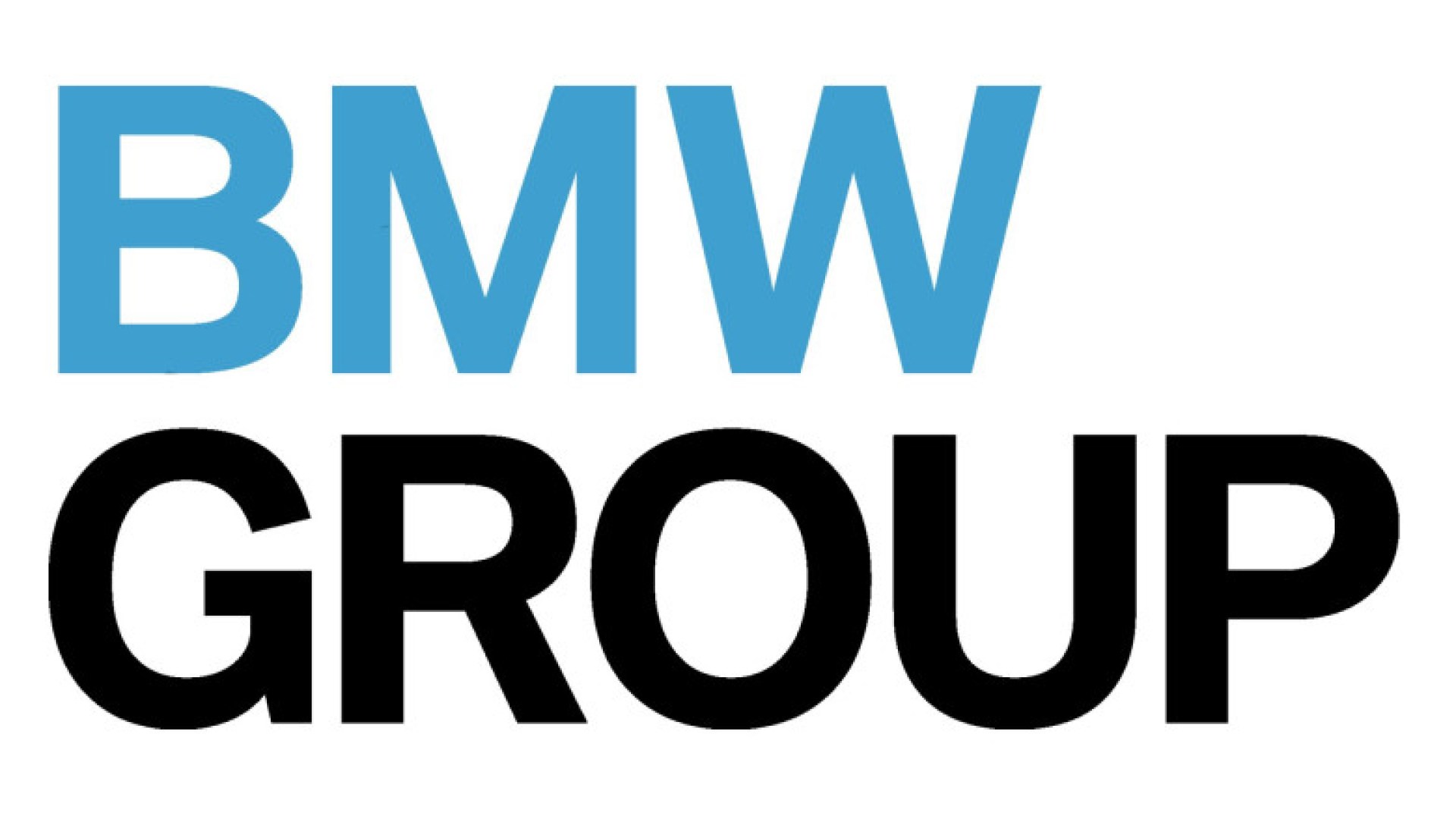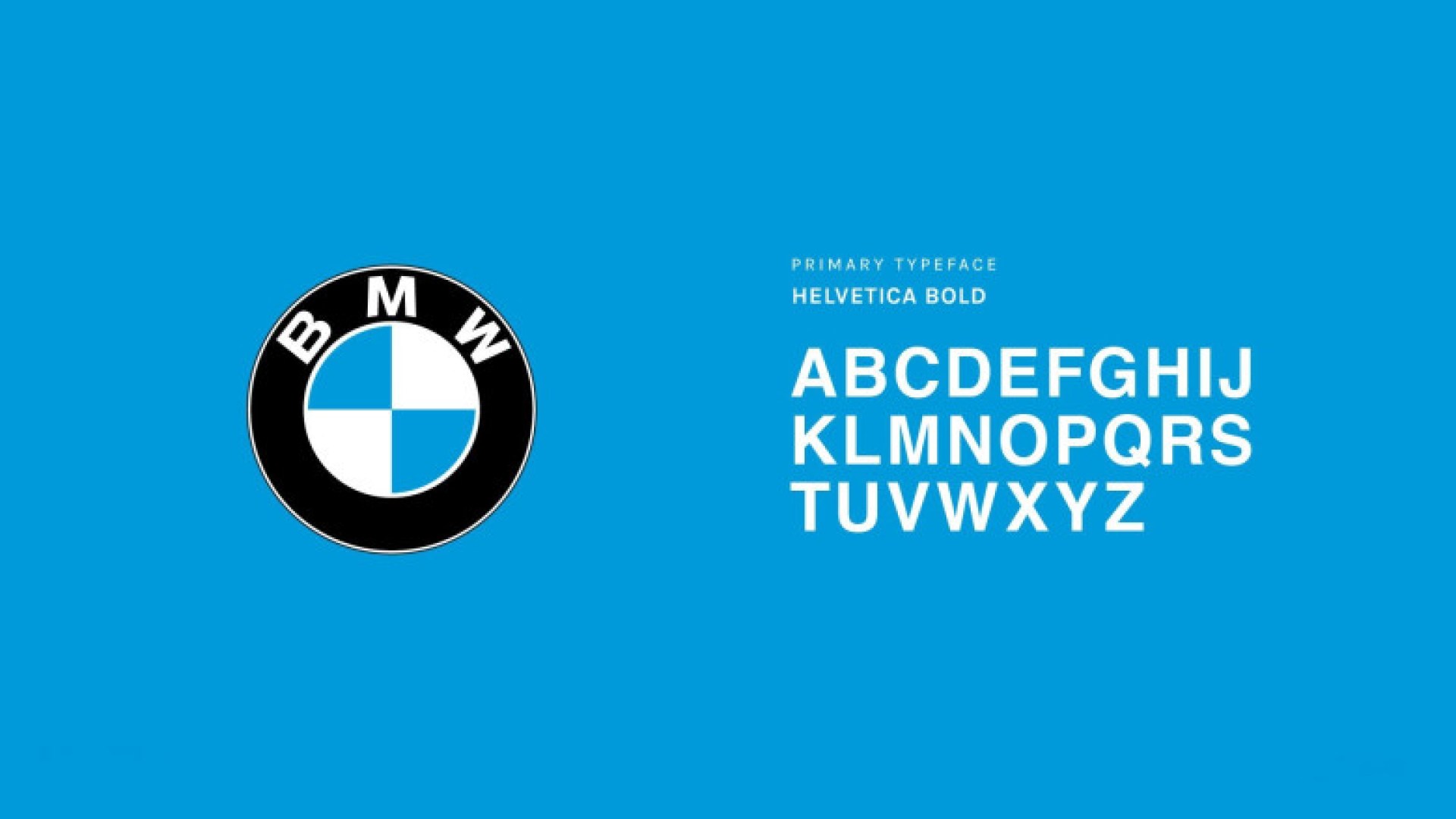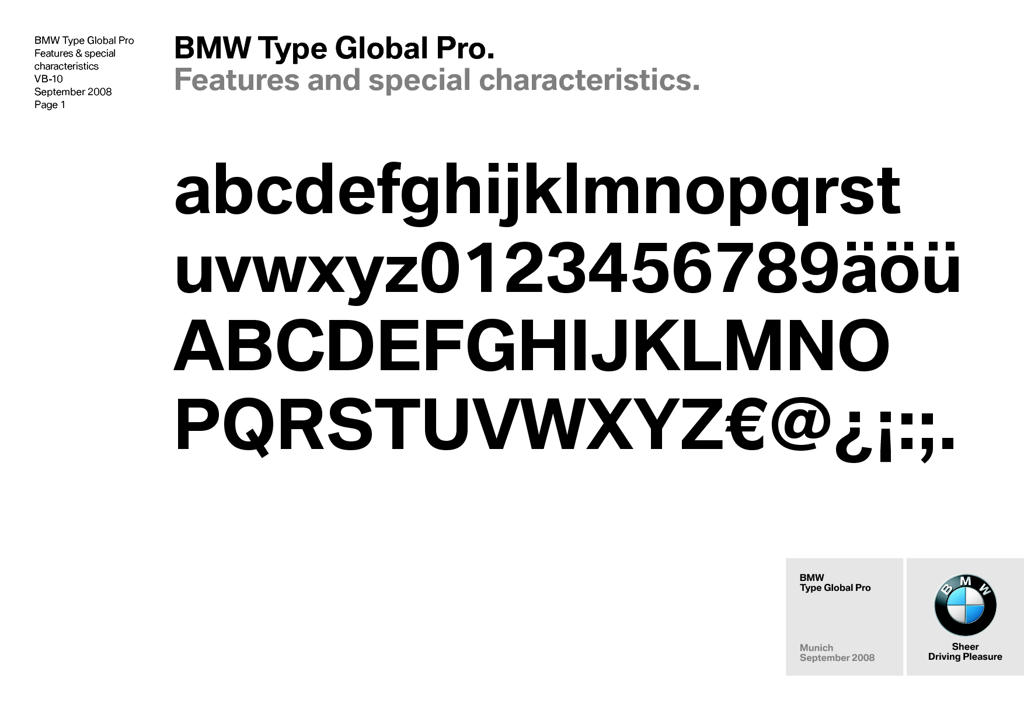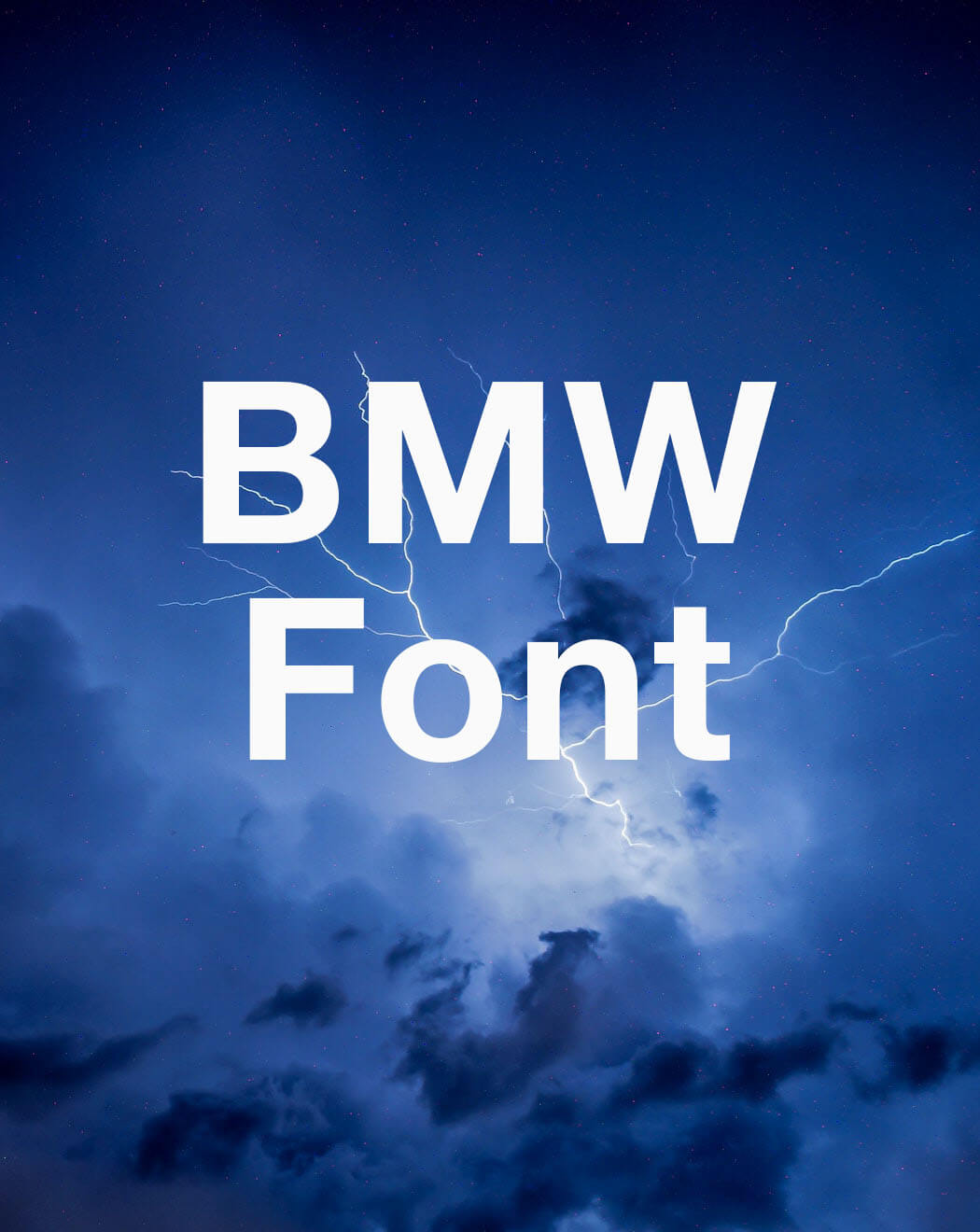
BMW Font: Khám Phá Bí Mật Đằng Sau Kiểu Chữ Huyền Thoại Của Thương Hiệu Xe Sang
Khi nhắc đến BMW, người ta thường nghĩ ngay đến những chiếc xe sang trọng, hiệu suất cao và thiết kế tinh tế. Nhưng ít ai biết rằng, đằng sau logo hình tròn quen thuộc và dòng chữ “Bayerische Motoren Werke” là cả một câu chuyện dài về kiểu chữ (font chữ) mang tên BMW Font. Đây không chỉ là một bộ ký tự đơn thuần, mà còn là linh hồn của thương hiệu, góp phần tạo nên bản sắc nhận diện mạnh mẽ qua hơn một thế kỷ. Trong bài viết này, chúng ta sẽ đi sâu vào khám phá mọi khía cạnh của BMW font, từ lịch sử hình thành, đặc điểm nhận dạng, cho đến cách ứng dụng trong thiết kế đồ họa và marketing.
BMW Font Là Gì? Giải Mã Bản Chất Của Kiểu Chữ Biểu Tượng
BMW font thực chất là một thuật ngữ dùng để chỉ hệ thống kiểu chữ chính thức được tập đoàn BMW sử dụng trong toàn bộ hệ thống nhận diện thương hiệu. Không giống như nhiều hãng xe khác chỉ dùng một font duy nhất, BMW đã phát triển một bộ nhận diện chữ viết riêng biệt, kết hợp giữa nét cổ điển và hiện đại. Kiểu chữ này xuất hiện trên logo, biển số xe, tài liệu quảng cáo, website và thậm chí cả giao diện hệ thống thông tin giải trí trên xe.
Bản chất của BMW font nằm ở sự cân bằng hoàn hảo giữa tính dễ đọc và tính thẩm mỹ cao. Các đường nét được thiết kế sắc sảo, không quá cầu kỳ nhưng vẫn toát lên vẻ sang trọng, đẳng cấp. Điều này phản ánh triết lý “Sheer Driving Pleasure” – niềm vui lái xe thuần khiết mà thương hiệu muốn truyền tải.
Lịch Sử Hình Thành Và Phát Triển Của BMW Font
Nguồn Gốc Từ Kiểu Chữ Helvetica
Trong giai đoạn đầu thế kỷ 20, BMW sử dụng các kiểu chữ phổ biến thời bấy giờ như Helvetica và Univers. Helvetica, với thiết kế sans-serif trung tính, dễ đọc, đã trở thành lựa chọn chủ đạo cho logo và các ấn phẩm chính thức. Tuy nhiên, khi thương hiệu phát triển, nhu cầu về một bộ nhận diện độc quyền trở nên cấp thiết.
Sự Ra Đời Của BMW Type
Vào những năm 2000, BMW hợp tác với các nhà thiết kế font chữ hàng đầu để tạo ra “BMW Type” – một bộ font chữ tùy chỉnh dựa trên nền tảng Helvetica nhưng được tinh chỉnh để mang đậm dấu ấn riêng. BMW Type có các biến thể như BMW Type Regular, Bold, Light, và Italic, phục vụ cho nhiều mục đích sử dụng khác nhau. Điểm khác biệt lớn nhất là tỷ lệ chữ được điều chỉnh để tăng tính nhận diện, đặc biệt là ở các ký tự như “B”, “M”, “W”.
Phiên Bản Hiện Đại: BMW Font Ngày Nay
Ngày nay, BMW font đã được số hóa và chuẩn hóa hoàn toàn. Bộ font chính thức bao gồm BMW Type Next, một phiên bản cập nhật với nhiều trọng lượng (weight) hơn, hỗ trợ đa ngôn ngữ và tối ưu cho màn hình kỹ thuật số. BMW cũng sử dụng các font chữ phụ trợ như BMW Helvetica cho các ứng dụng văn bản thông thường, nhưng BMW Type vẫn là linh hồn của thương hiệu.
Đặc Điểm Nhận Dạng Của BMW Font
Để nhận biết BMW font một cách chính xác, bạn cần chú ý đến những đặc điểm sau:
• Kiểu dáng Sans-serif: Không có chân (serif), tạo cảm giác hiện đại, sạch sẽ và dễ đọc trên mọi chất liệu.
• Tỷ lệ chữ hài hòa: Chiều cao chữ (x-height) lớn, giúp tăng khả năng đọc ở khoảng cách xa.
• Đường cong tinh tế: Các nét cong như ở chữ “C”, “G”, “S” được thiết kế mềm mại nhưng vẫn giữ được độ chính xác.
• Khoảng cách chữ (kerning) chuẩn xác: Khoảng cách giữa các ký tự được tối ưu để tạo sự cân bằng thị giác, đặc biệt quan trọng trong logo BMW.
• Tính nhất quán: Mọi biến thể của font đều giữ nguyên DNA thiết kế, từ phiên bản in ấn đến kỹ thuật số.
Phân Loại Các Biến Thể Của BMW Font
BMW font không chỉ có một phiên bản duy nhất.
• Tính nhất quán toàn cầu: Dù ở bất kỳ quốc gia nào, BMW font vẫn giữ nguyên hình dáng, đảm bảo thông điệp thương hiệu được truyền tải đồng nhất.
• Tối ưu trải nghiệm người dùng: Font chữ dễ đọc, thân thiện với mắt, giúp khách hàng dễ dàng tiếp cận thông tin.
• Giá trị thẩm mỹ cao: Thiết kế tinh tế góp phần nâng tầm giá trị sản phẩm và dịch vụ.
Hạn Chế
• Không có sẵn cho công chúng: BMW font là tài sản trí tuệ của tập đoàn, không được phép tải về miễn phí. Điều này gây khó khăn cho các nhà thiết kế muốn sử dụng trong các dự án cá nhân.
• Chi phí bản quyền cao: Nếu muốn sử dụng hợp pháp, bạn phải trả phí bản quyền hoặc thông qua đối tác được ủy quyền.
• Giới hạn sáng tạo: Việc bắt buộc tuân thủ một bộ font duy nhất có thể hạn chế sự đa dạng trong thiết kế.
So Sánh BMW Font Với Các Font Chữ Xe Hơi Khác
Để hiểu rõ hơn về vị thế của BMW font, hãy so sánh với một số đối thủ:
Thương HiệuFont Chữ ChínhĐặc Điểm Nổi Bật
BMWBMW Type / BMW Type NextSans-serif, tinh tế, cân bằng, hiện đại
Mercedes-Benz Corporate FontSans-serif, mạnh mẽ, góc cạnh hơn
AudiAudi TypeSans-serif, thanh lịch, khoảng cách chữ rộng
PorschePorsche NextSans-serif, thể thao, năng động
Có thể thấy, BMW font nổi bật nhờ sự cân bằng giữa vẻ đẹp cổ điển và hiện đại, trong khi các đối thủ thiên về cá tính riêng biệt hơn.